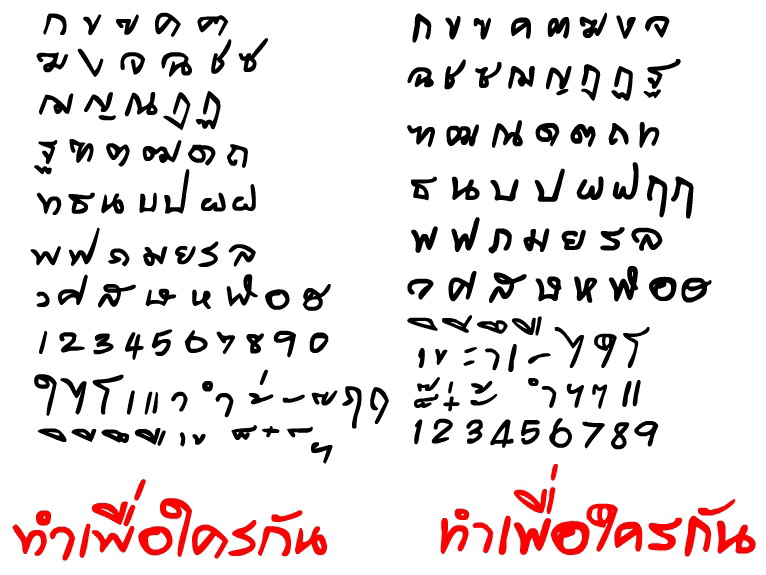
ซ้ายหรือขวา
รักพี่เสียดายน้องครับ
ชอบสองแบบเลย
แต่ใจเอนเอียงไปทางซ้าย
ทำทั้ง 2 แบบเลยสิคะ
สวยออกเนอะ  :25:
คำว่า ทำเพื่อใครกัน ด้านซ้ายดูมันกว่าครับ
แต่ทำ 2 แบบอย่างที่นุกบอกเลยก็ดี :22:
ซ้ายน่าจะดี....กว่า ถ้างั้นก็... :01:
ขวาก็สวยนะคะ
ชอบตัวอักษรทางขวาบางตัวด้วยนะ
ทำเป็น 2 เวอร์ชั่นเลยไงคะ  :25:
ทำทั้งสามแบบเลยครับ
แบบเดียวแล้วกัน นะ :01:
ชอบซ้ายมากกว่า แต่ทำสองเวอร์ชั่นเลยก็ดีนะ เท่ดี
ชอบบางตัวทางซ้าย และชอบหลายตัวทางขวา
เชียร์ฝั่งซ้ายครับ
ซ้าย
ขวา